디자이너 집중탐구 인터뷰
이름을 건 Rix락-시리즈 폰트, 국제 디자인 공모전에서 대상 수상
박용락 폰트 디자이너 @rakfont
20년 넘게 폰트 디자인 업계에 종사하며 대한민국 대표 폰트 디자이너로 자리매김했다. 2005년 공동 설립한 폰트디자인 전문회사 '폰트릭스'에 몸 담고 있는 디자이너이자 이사. 국내 굴지의 기업 삼성, CJ그룹, 네이버, 현대카드, 티몬, KBS, SBS, MBC, YTN 뉴스, 동아일보 등의 전용서체를 개발했다. 또한 상업용 서체 윤고딕과 윤명조 500, Rix고딕과 명조, Rix도로명 시리즈 등 지금까지 1,000 여종의 서체를 제작 및 디렉팅 했다.
폰트에 이름을 건다는 것은 어떤 의미일까. 그만큼 자신이 있다는 뜻이다. 22년의 짧지 않은 경력은 견고하고 기본에 충실한 그의 폰트에서 느껴진다. 회사의 폰트 네임 'RixFont'의 앞 자와 자신의 이름 끝 자를 딴 Rix락-Sans는 최신 경향을 고려한 꽉 찬 골격과 정돈된 글줄로 도시적이고 모던하다. Slab Serif(돌출된 형태가 두껍고 사각형 같은 세리프)를 접목한 Rix락-Serif는 좀 더 부드럽고 세련되며 중성적인 매력을 갖고 있다.
Rix락-시리즈 서체가 국제 대회에서 수상한 사실은 폰트 자체의 완성도를 넘어 세계에 한글의 아름다움을 알린 뜻깊은 성과이다. 국내에서 많은 이력을 가진 박용락 디자이너에게도 큰 의미로 다가올 것이라 생각된다. 폰트와 함께 성장해온 그의 이야기를 들어보자.
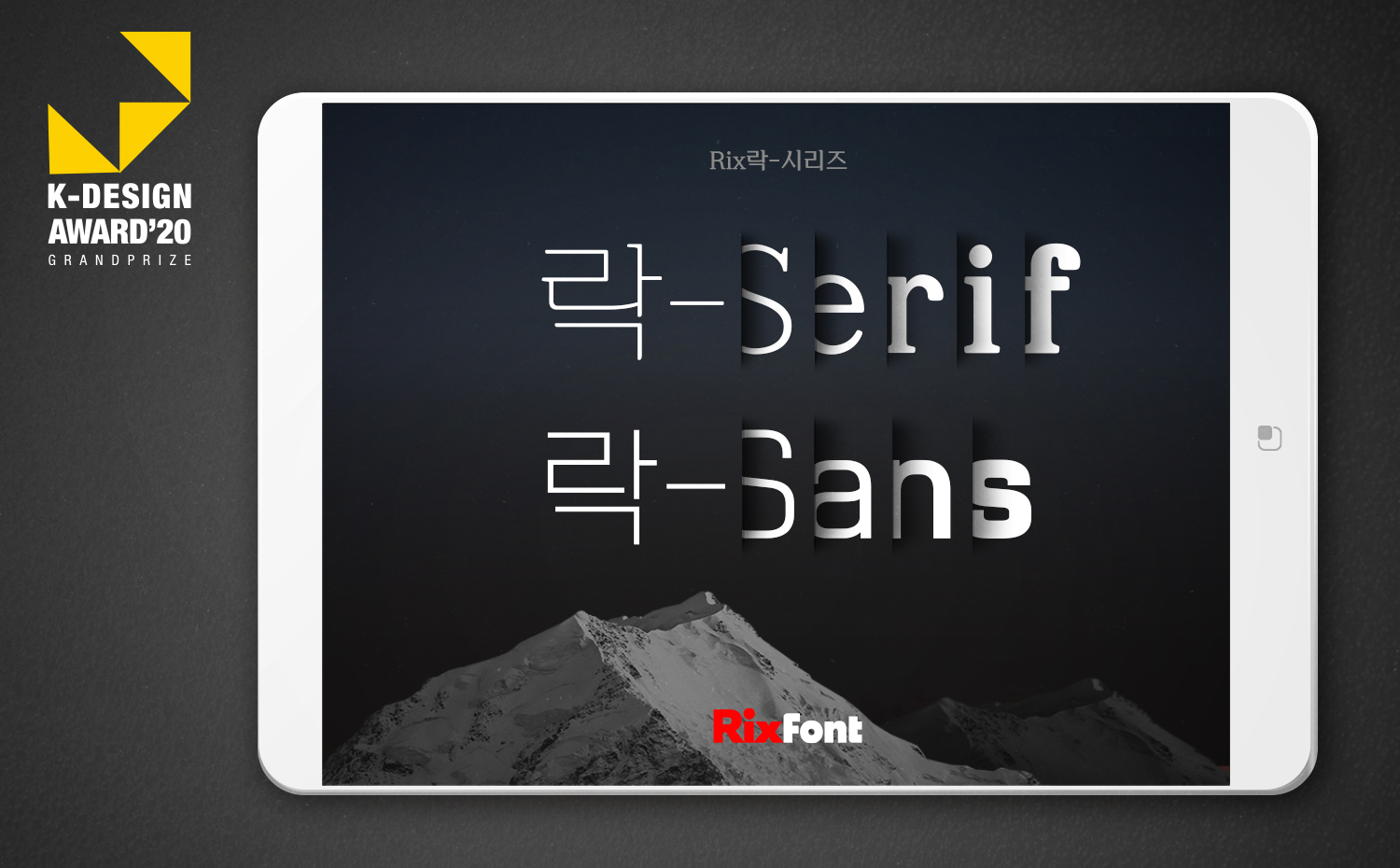
안녕하세요. 박용락 디자이너님. 먼저 'K-디자인 어워드 2020' Grand Prize (대상) 수상을 축하드립니다! 자신의 이름이 들어간 폰트라 더 감회가 새로우실 것 같은데 맨 처음 수상 연락을 받고 기분이 어땠나요?
쟁쟁한 2000여점이 넘는 작품이 출품되었다고 하는데.. 그중 1%만 주는 대상에 선정되었다니 믿기 힘들더군요. 지금까지 열심히 폰트 디자인을 해왔던 것에 대한 보상을 받은 것처럼 기뻤습니다.
'K-디자인 어워드'에 대해서는 어떻게 알게 되어 공모전 신청까지 생각하시게 되었나요?
페이스북을 통해서 알게 되었습니다. 작년에 중국의 한자 폰트가 상을 탄 것을 보고 한글 폰트도 상을 타야 되지 않겠냐는 생각을 하였습니다. 마침 Rix락시리즈의 출시 일정과 잘 맞아떨어져서 출품하게 되었습니다.
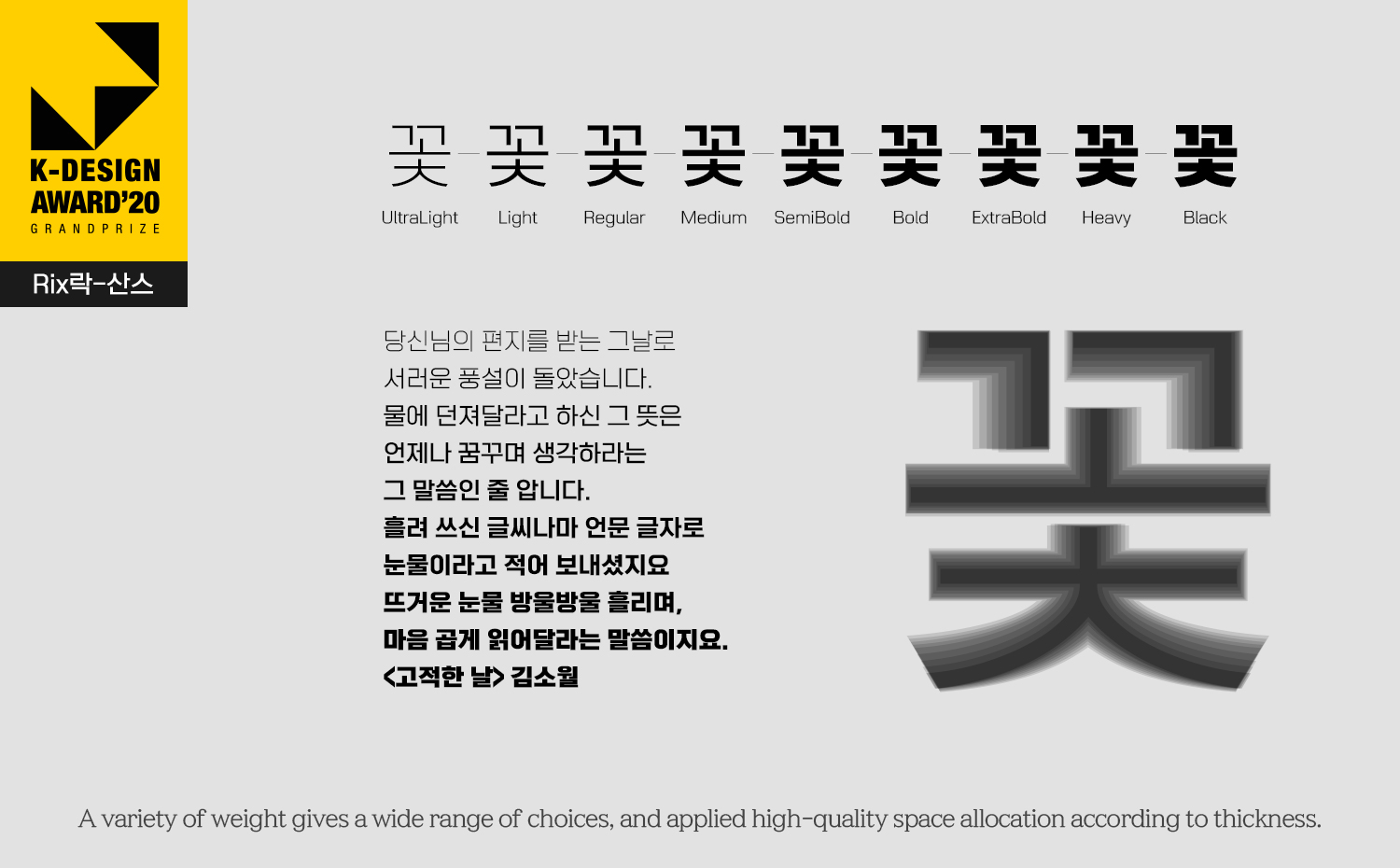
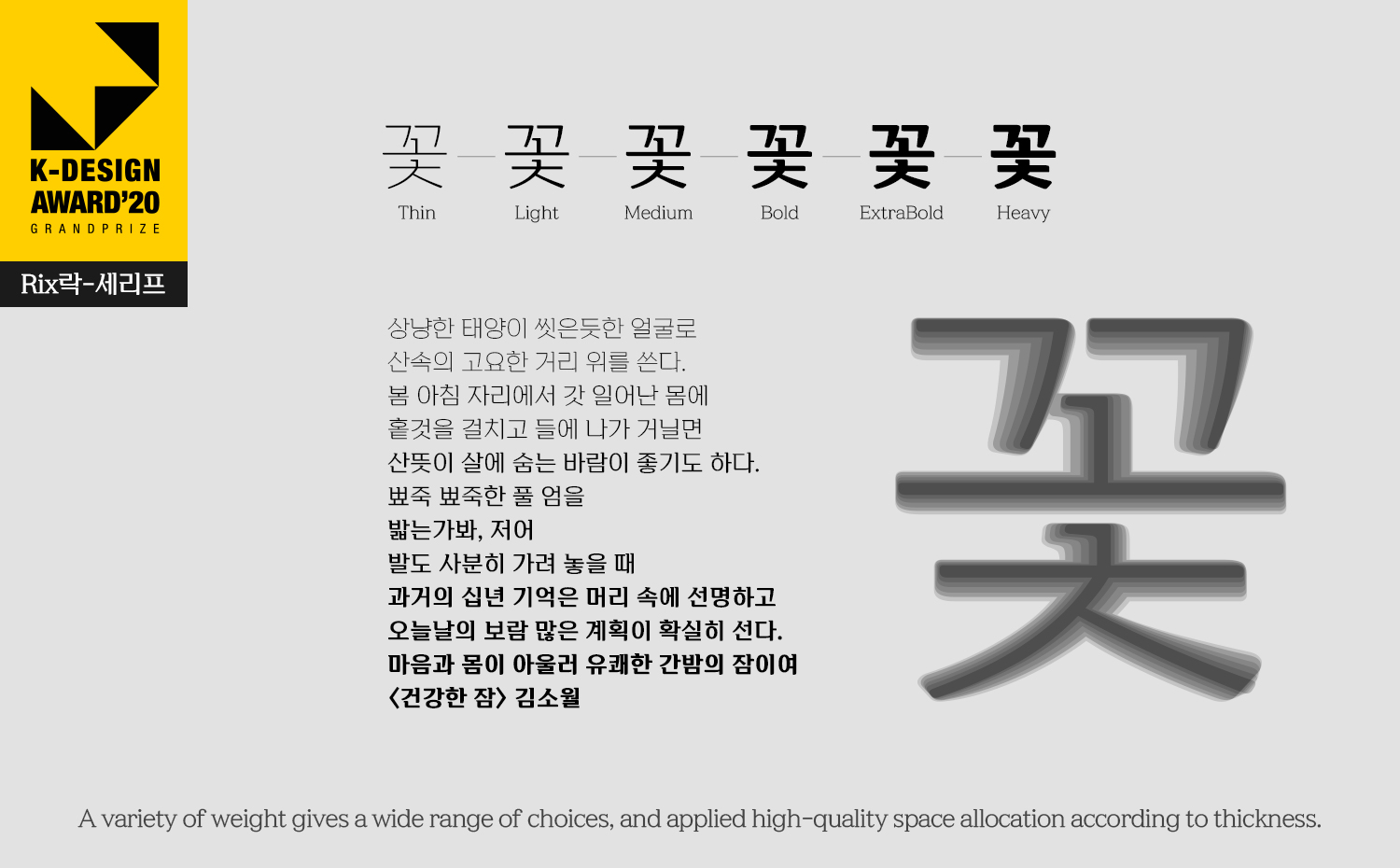
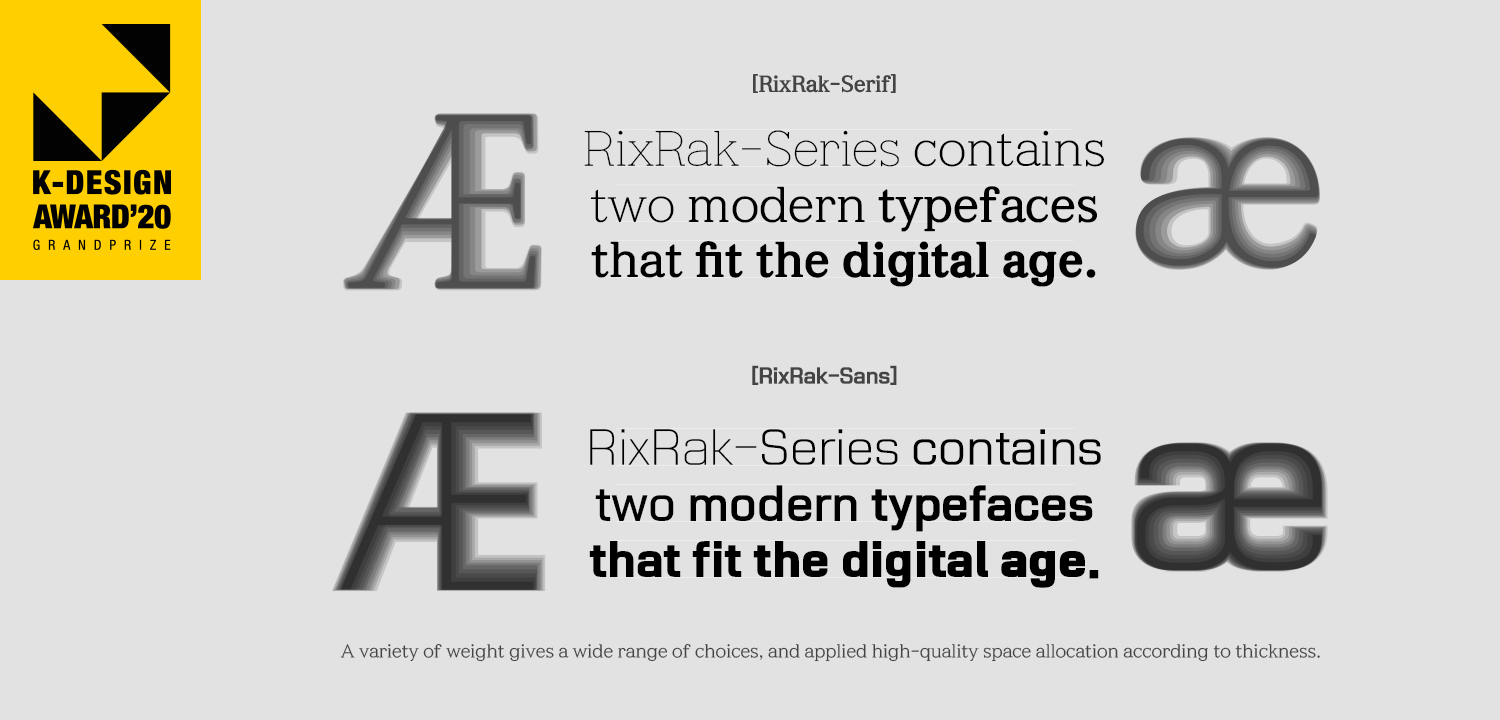
Rix락-Sans, Rix락-Serif 모두 다소 생소한? 독특한 폰트명이라고 느껴져요, 이름의 끝자를 폰트명에 쓰게 된 배경이 궁금합니다.
폰트릭스의 대표 시그니쳐 폰트가 필요한 시점이었습니다. 폰트 이름에 디자이너의 이름을 붙이는 것은 도자기나 공예품과 같은 제품을 만드는 장인들이 자기 이름을 걸고 제품을 만드는 것과 같다고 보시면 됩니다. Rix락 시리즈도 제 이름 중 락을 붙일 정도로 모든 노하우와 열정을 다해 제작하였습니다.
Rix락-시리즈 폰트가 기존의 폰트들과 다른 무엇, 특별히 담고 싶었던 메시지나 의미가 있었다면?
경험상 감정을 최대한 자제한 건조하고 중립적인 글꼴들이 오랜 시간 사용해도 질리지 않고 많이 사용되는 것을 보아 왔습니다. 기존에 나와 있는 꽉 찬 골격의 서체와 완전히 다른 차별화된 서체라고 말씀드릴 수 없지만, 향후 질리지 않고 오래 쓸 수 있는 서체 중 대표 폰트가 되길 바라는 의미로 제작했습니다.
'한 놈만 팬다'는 말이 다소 격할 수 있지만(웃음) 그 정도로 오랜 기간 폰트만을 연구하고 꾸준히 해오셨는데요, 폰트의 어떤 매력 때문에 이 일을 계속하고 있다고 생각하시는지?
CI나 BI 디자인은 몇 글자의 디자인만 몰입해서 디자인하면 되는 반면 폰트 디자인은 몇 글자 아이데이션 후에 정말 지루하고 힘든 일이 기다리고 있습니다. 한글의 글자 수가 11,172나 되니 말입니다. 이 지루한 과정 때문에 많은 후배 디자이너가 다른 일을 찾아 떠나기도 했습니다. 정말 힘이 들었지만 폰트로 제작되어 누군가에 의해 쓰이는 것을 봤을 때 가장 큰 기쁨을 느낍니다. 또한 폰트는 영속성이 있어서 어떠한 디자인 제작물보다 오래도록 지속되는 힘을 가지고 있는 것이 큰 매력입니다.
마지막으로, 박용락 디자이너의 다음 스텝, 가장 가까운 목표는 무엇인가요?
본문형 서체의 새로운 페라다임을 제시할 수 있는 폰트를 제작하고 싶습니다. 지금까지는 거의 비슷한 고딕이나 명조를 사용해 왔습니다. 그와 다른 스타일이면서 가독성이 높아서 본문형으로 사용할 수 있는 폰트를 제작하는 것이 목표입니다. 그밖에 폰트릭스가 가지고 있는 베리어블 폰트, 압축 폰트, Mix폰트, 보안 폰트, 인감 폰트와 같은 기술을 이용하여 사업화를 진행하고 싶습니다.